异体这个术语在《汉书·艺文志》中就有了:“史籀篇者,周时史官教学童书也,当孔氏壁中古文异体。”这里的“异体”还是书体差异层面的。《说文》段注中也用到这个术语,如《说文·肉部》:“胞,小冥易断也。从肉,绝省声。”段注:“脆、腈盖本一字异体,《篇》、《韵》皆云‘胞同臃’。”这里的“异体”跟现在的概念一致。汉字异体问题较为复杂,光是异体字的定义就各有不同,略举几家如下:
1.王力主编的《古代汉语》(中华书局,1981年)给异体字的定义是:两个(或两个以上的)字的意义完全相同,在任何情况下都可以互相代替。
2.刘又辛在《大型汉语字典中的异体字、通假字问题》(收入《文字训诂学论集》,中华书局,1993年)一文中把异体字定义为:异体字记录语言中同一个词,是功能相同而形体不同的字。
3.赵振铎1996年在《辞书研究》上发表《谈异体字》-文,把异体字定义为:异体字是一个字的不同写法,异体字是音义相同字形不同的字。
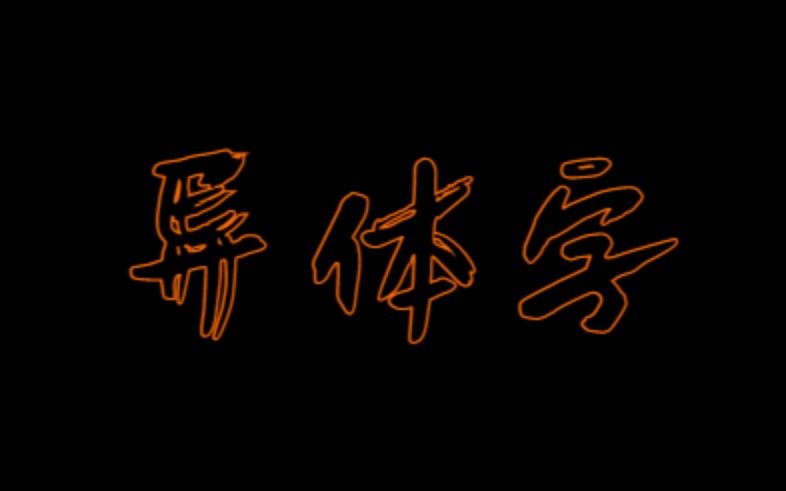
4.刘志基在《汉字异体字论>(见李圃主编的《异体字典》,学林出版社,1997年)一文中把异体字定义为:异体字是书体不同的字,是指今体字与古体字说的。
定义2、3都谈到字形不同,定义4也是字形不同,实际上就是“异形字”,上文已经对“异形字”作过分析。定义1过于绝对化,“在任何情况下都可以互相代替”的字恐怕是没有的,这样限制“异体字”的范围与异体字的实际情形是不相吻合的,因为异体字往往是由于时间或地域的不同而产生的,而且不同的时代会有异体字的分化与合并的现象。
我们主张在一定的时代背景上看待异体字问题,也就是说,异体字是有时代特点的。上文所引刘志基《汉字体态论》中关于异体字的分化与合并现象足以说明问题了,刘志基这样概括说:“如果说同字异体这一汉字体态特征本身还有什么基本特征的话,那便是它的历时流变性质。纵观汉字演变史,不难发现,许多异体是忽生忽灭,流行一时即遭淘汰的。因此,历史上的许多异体,早已是鲜为人知的陈迹了。倘若调查汉字个体发生发展的全部历史过程,又可发现,异体的兴废是一种持续不断的新陈代谢流程。如果细审字体的历时更替,则还可看到这种更替又是造成异体的一个途径。然而,最能凸现汉字异体历时流变特征因由的,当推一些较为特殊的字形演化现象,即分解、转移、合并等。”
建立这样一种时代观念,立足于异体字在不同的时代的分合,就能较清晰地把握异体字的种种规律,就能破除所谓“狭义异体字”“交错式异体字”“包孕式异体字”等等现象,从而有利于异体字的深入研究。从这个意义上讲,我们主张把异体字定义为:异体字是指在一定的历史时期内,音义相同但字形结构不同的字。
我们把书体的不同排除在异体字范围之外,那是因为这个方面的不同对于汉字异体字的整理和规范没有多少意义,而凡也会无限制地扩大异体字的范围。